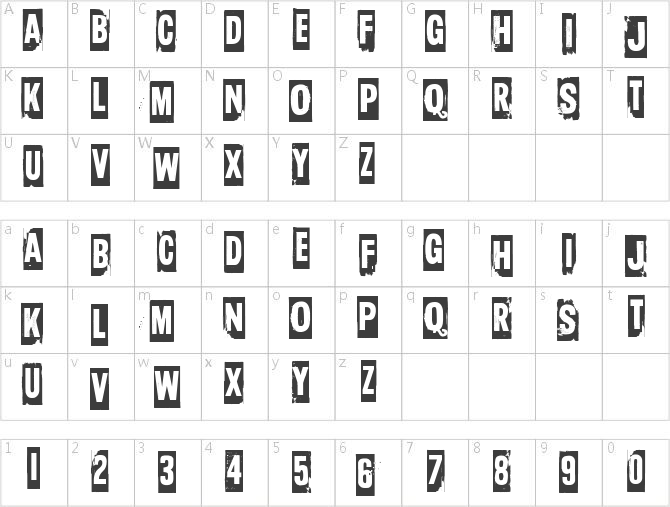
Too drunk to fuck
Too drunk to fuck字體字庫(kù)是一款讓人賞心悅目、百看不厭的英文字體,適合各類廣告和產(chǎn)品包裝設(shè)計(jì)應(yīng)用,字體大小0.37MB,格式為ttf字體,上傳用戶是錦程正陽(yáng),作者/版權(quán)方為未知